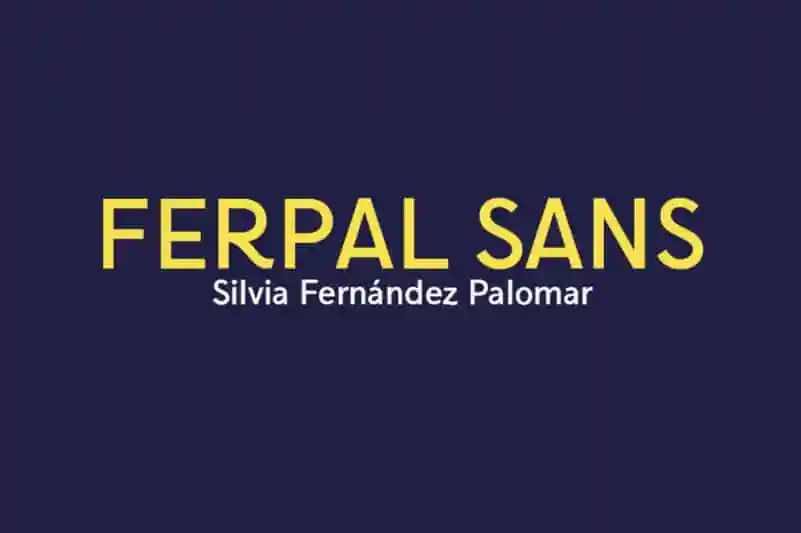
Introduzimos uma família de tipos gerais para o nosso tempo, chamada Ferpal Sans Font. Este tipo foi criado pelo designer Silvia Fernández Palomar especialmente para Madrid, um dos centros urbanos mais vibrantes e diversificados do mundo. Desenvolvido a partir da falta de identidade e homogeneidade encontradas na tipografia local, o Ferpal é projetado principalmente para sinalização. Ele baseia-se nos sinais cerâmicos das ruas de Madrid e nas padrões de design da tipografia aplicada em grandes ambientes. Este tipo é perfeitamente adaptável a uma ampla variedade de aplicações gráficas, desde editoriais até produtos. Ferpal Sans Font é uma escolha ideal para qualquer designer buscando unificar sua identidade visual e transmitir a essência da cidade de Madrid no design digital. Seja em um layout web minimalista ou em uma peça publicitária com um tom mais vibrante, Ferpal Sans consegue criar um impacto intenso que ajuda a destacar seus projetos na cena do mercado moderno.